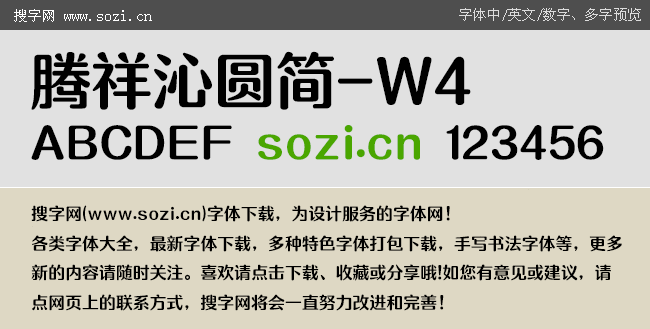
騰祥沁圓簡-W4
搜字網(wǎng)提供一款騰祥沁圓簡-W4中文藝術(shù)字體下載,騰祥沁圓簡-W4是一款應(yīng)用于廣告創(chuàng)意設(shè)計(jì)方面的中文簡體字體,該字體線條粗細(xì)適中,字形端正大方得體,整體效果非常的出眾,可以應(yīng)用于橫幅標(biāo)語、美術(shù)設(shè)計(jì)、宣傳海報(bào)、圖形設(shè)計(jì)等領(lǐng)域。